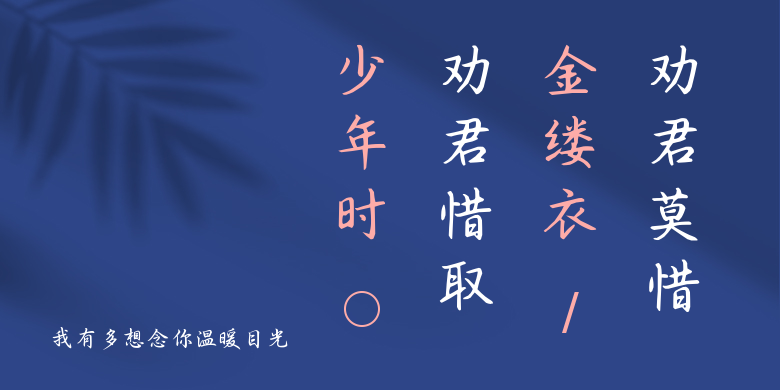
我有多想念你温暖目光
我有多想念你温暖目光,这款字体结构工整、笔画清晰,兼顾美观与易读性,适用于标题、正文、海报、包装、LOGO 等多种场景。字形优雅稳定,风格百搭耐看,适配日常排版与创意设计,让文字呈现更舒适、更具质感。我有多想念你温暖目光一笔一画,皆是细节,以均衡的比例、流畅的线条打造舒适视觉体验,字形端正大气,风格简约现代。无论是商业设计、品牌宣传还是日常排版,都能轻松驾驭,让文字更有格调与力量。我有多想念你温暖目光字体下载。